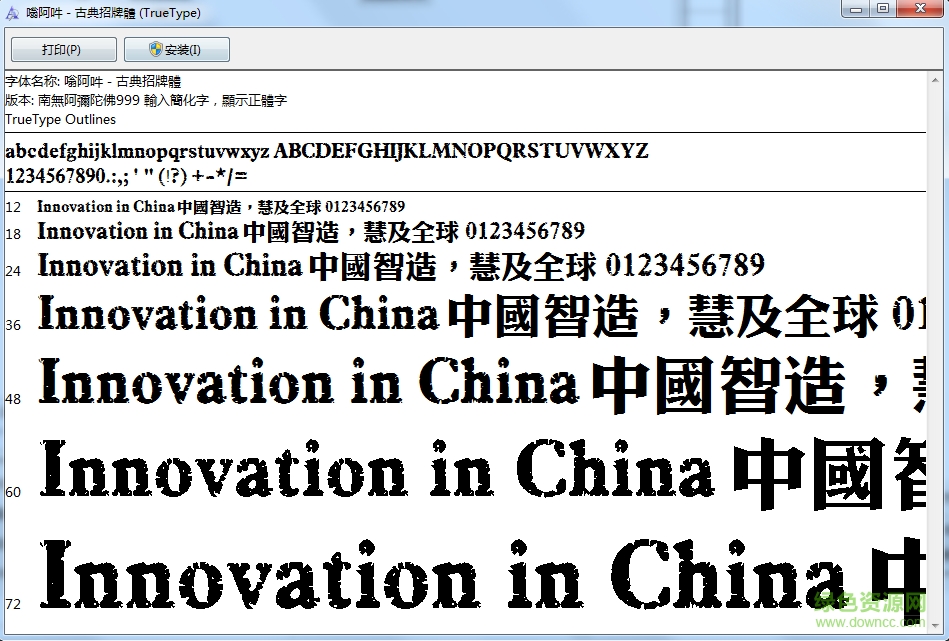
软件介绍 软件标签: 古典招牌体 字体 古典招牌体是一款古代韵味的招牌使用的书法字体,支持繁体输入,很有古色古香的风味,喜欢的朋友欢迎来绿色资源网免费下载!古典招牌体字体安装说明在绿色资源网下载本款字体后,右键点击安装接即可。小编点评古典招牌体可用于古典牌匾设计、百年老字号招牌制作等,绿色清新风格简约漂亮大方的一款艺术字体。其他系统说明Windows XP(2000\98)系统:把解压好的字体文件放入 C:\Windows\Fonts 目录中即可。Win Vista\Win 7\Win 8系统:鼠标右键单击字体文件,然后点击 > "Install" 安装字体。 软件截图 上一张下一张(1 / 1) 安装详细截图 其他版本下载 标题 大小 更新日期 下载 下载地址 电脑版 古典招牌体 点击报错 软件无法下载或下载后无法使用,请点击报错,谢谢! 关闭报错反馈 请描述您所遇到的错误,我们将尽快予以修正,谢谢! *必填项,请输入内容 本类最新 dreamweaver字体库 首尔南山体字体 v1.06 官方版 潮字社风云简ttf 潮字社凌渡鲲鹏简体字体 潮字社曾玉波手书简字体 微博慧心字体 相关文章 Photoshop字体安装使用方法和技巧 如何解决“无法新增字体”问题 Win 7系统安装字体方法 网页字体大小设置方法 怎么改网页字体大小 在Linux系统中安装字体的几种方法 windows7字体显示问题:打开某些程序的时候显示的是乱码 用户评论 热门评论 最新评论 发表评论 查看所有评论(0) 昵称: 请不要评论无意义或脏话,我们所有评论会有人工审核. 字数: 0/500 (您的评论需要经过审核才能显示)